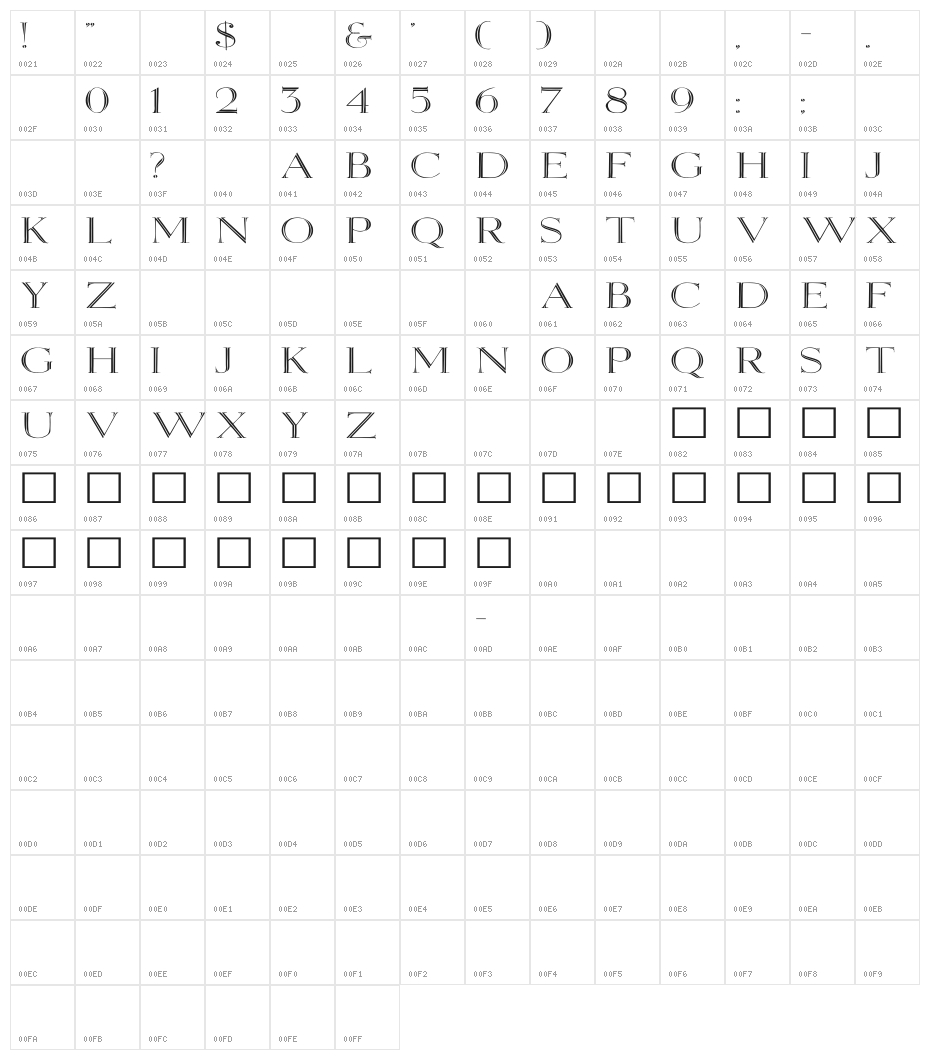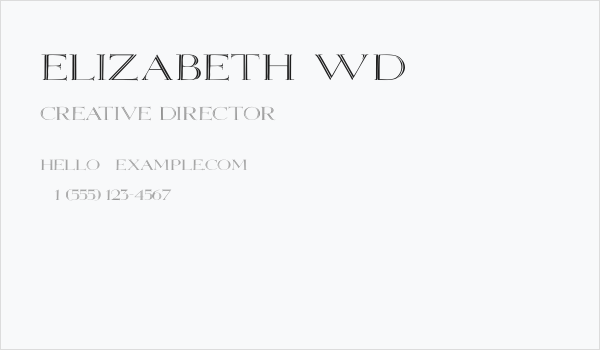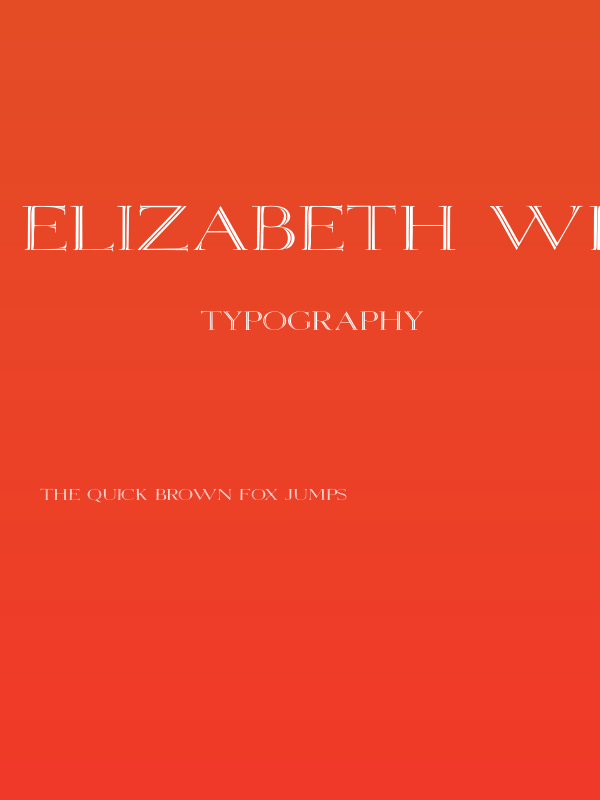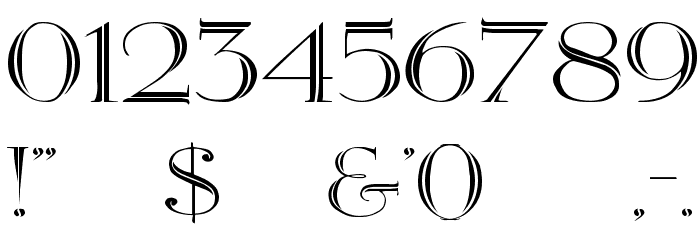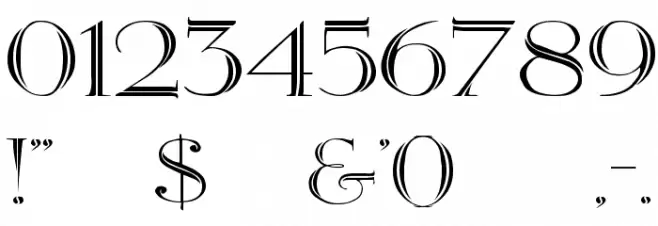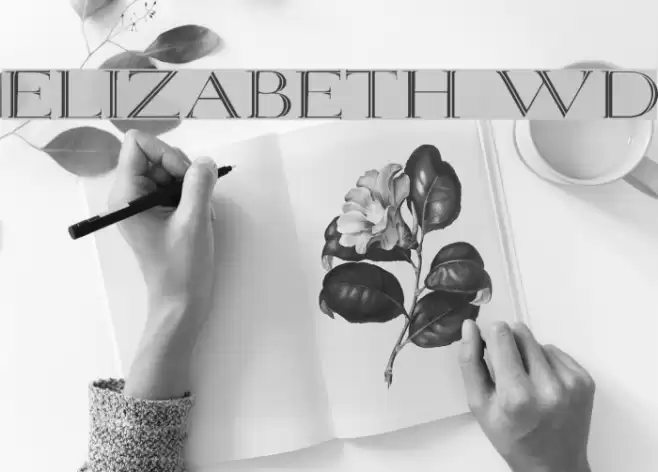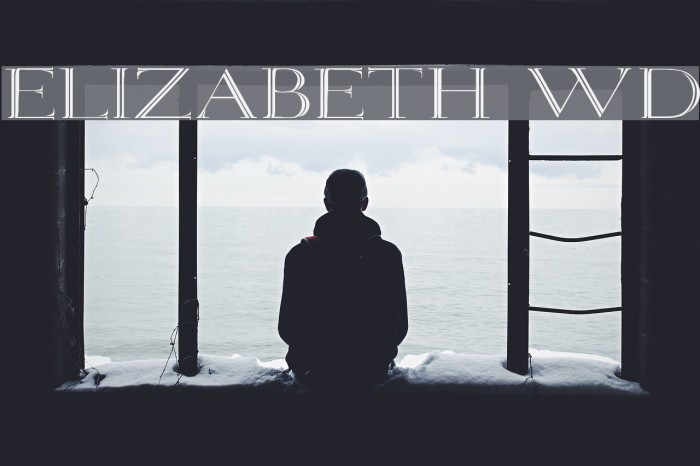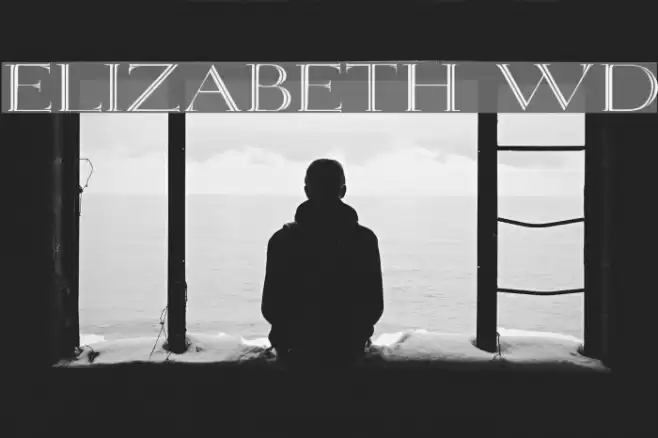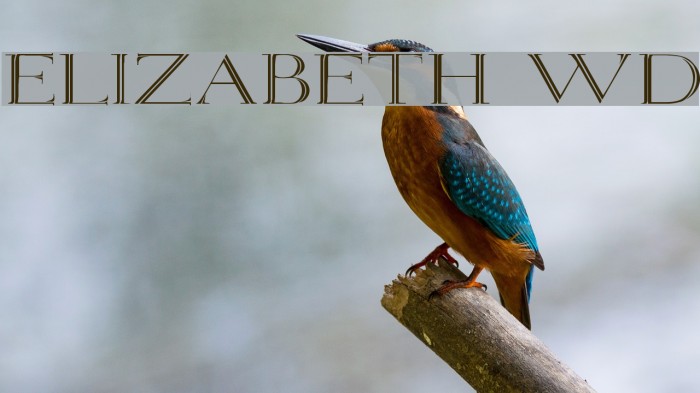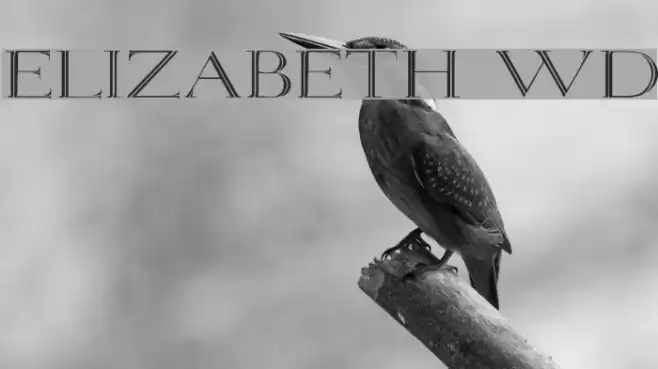
Elizabeth Wd Font
Fonts by David Rakowski
| Caso d'uso | Headlines, Logos, Editorial design |
| Progetti proposti | Ideal for luxury branding, editorial design, wedding invitations, and high-end product packaging. |